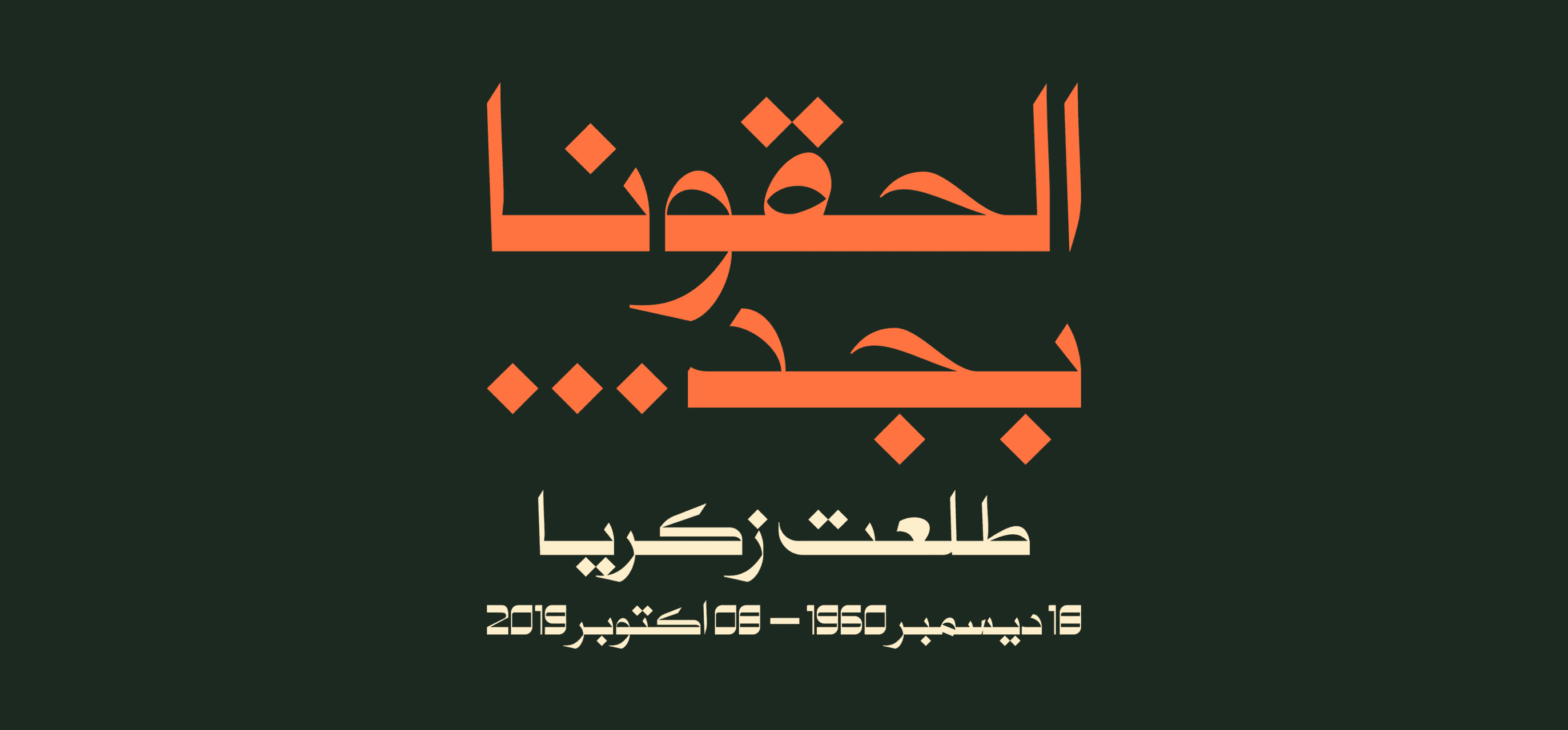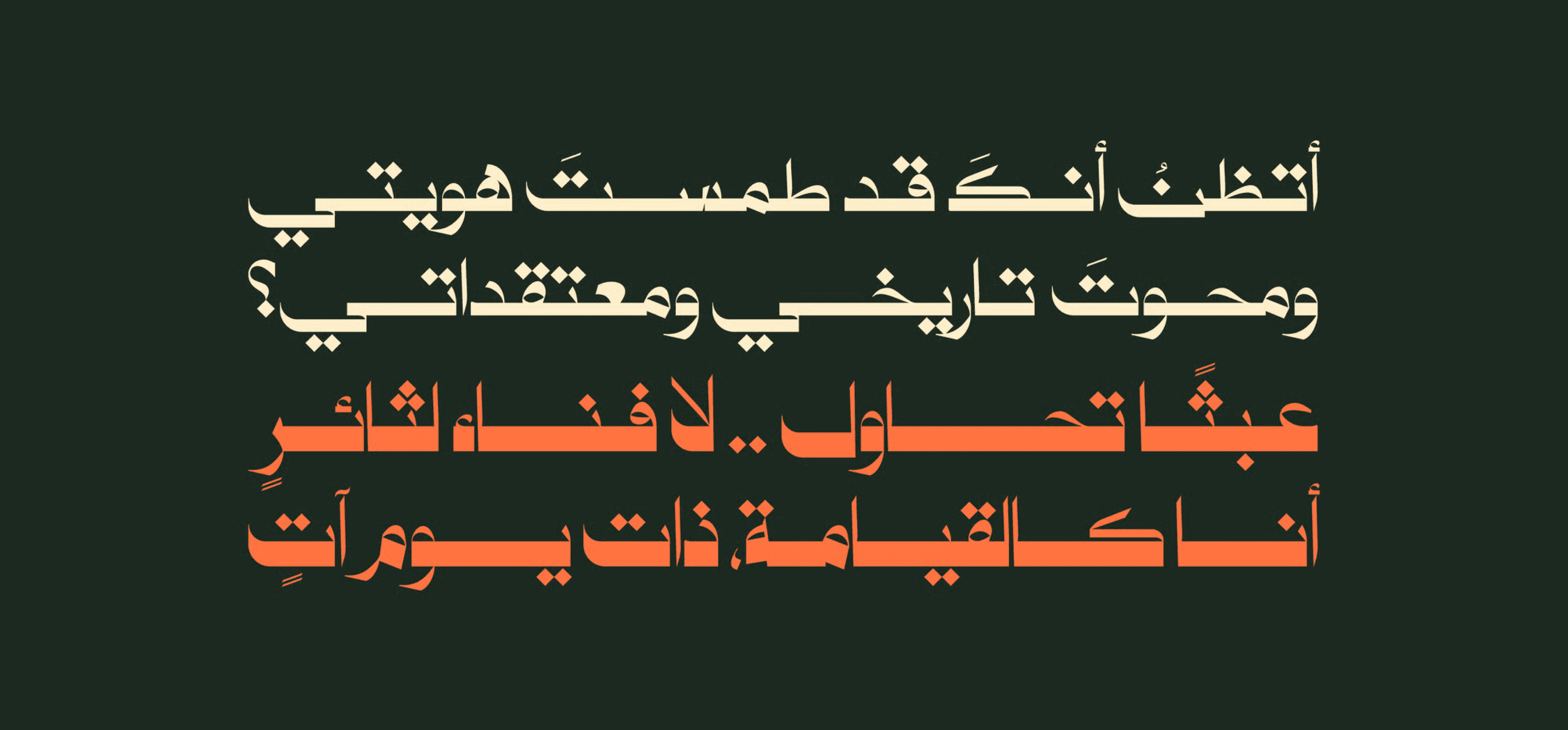
هو خط عربي يجمع بين الحداثة والطابع التقليدي، يتميز بنقاط كبيرة وحروف ممتدة بأناقة. يوازن Kahaza بين الحدة والنعومة، ويأتي بنسختين مختلفتين من حيث وزن خط الأساس: Regular لمظهر نظيف ومصقول، وBold لإطلالة أكثر قوة وتأثيراً.